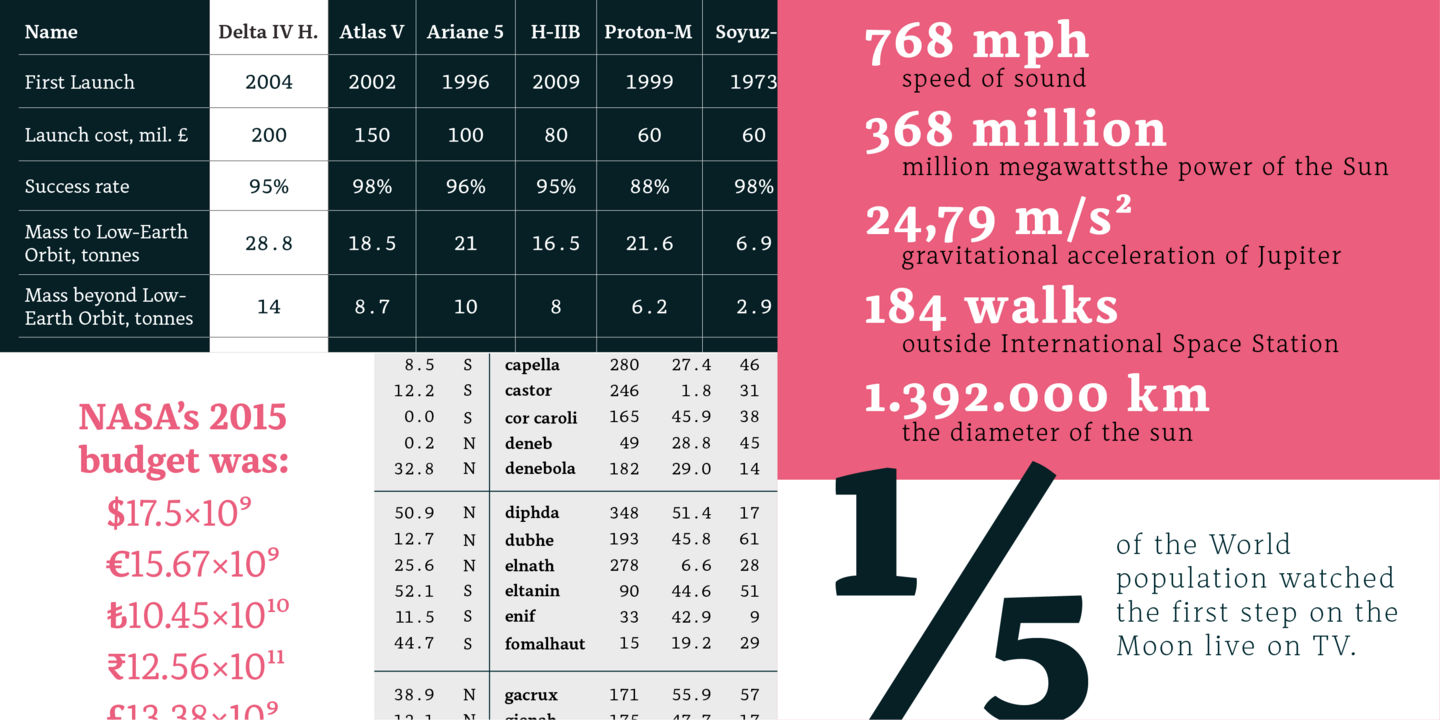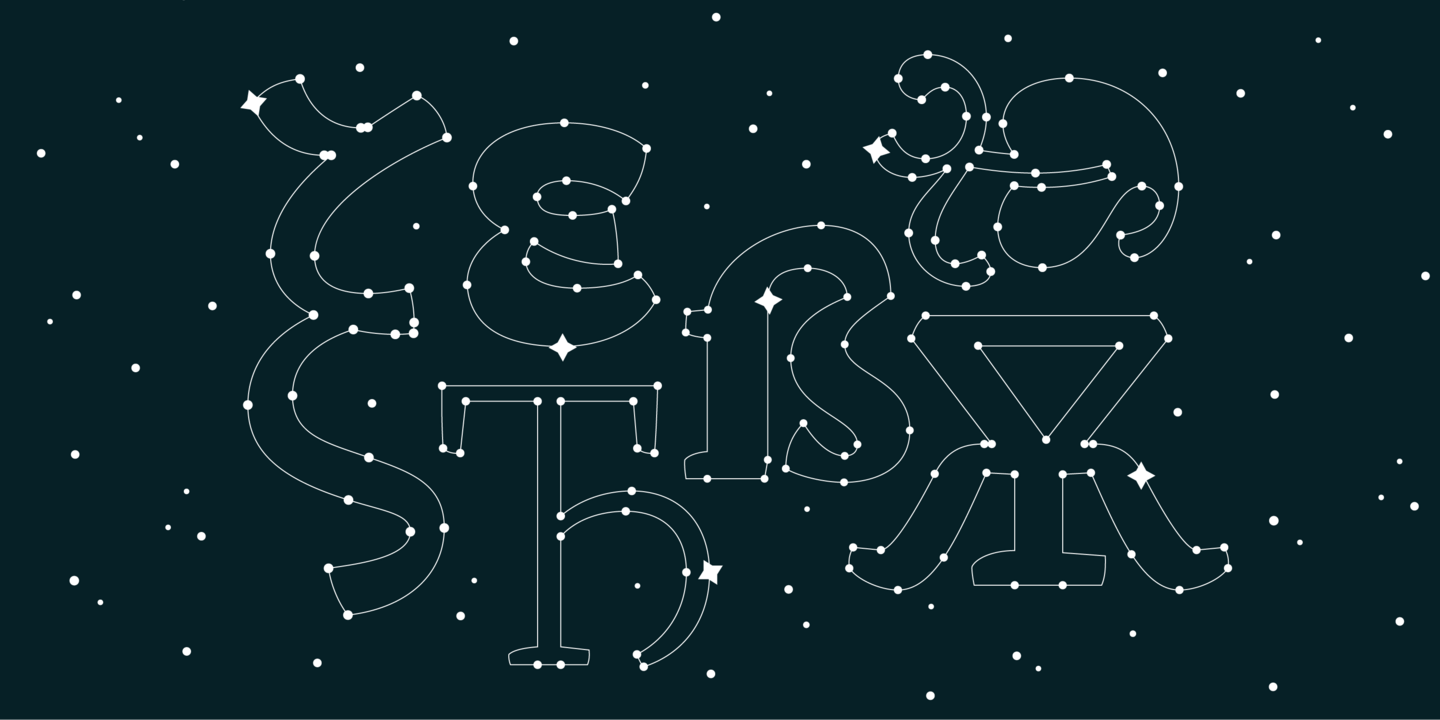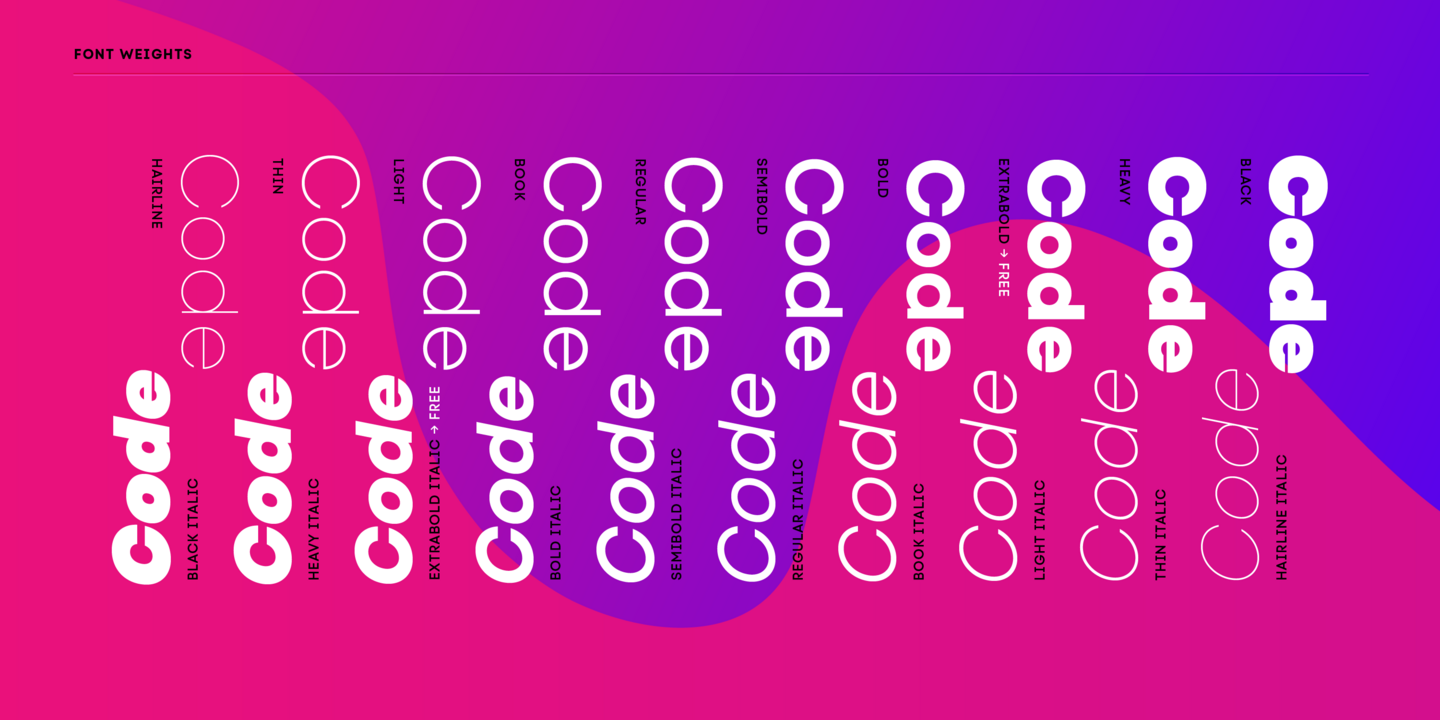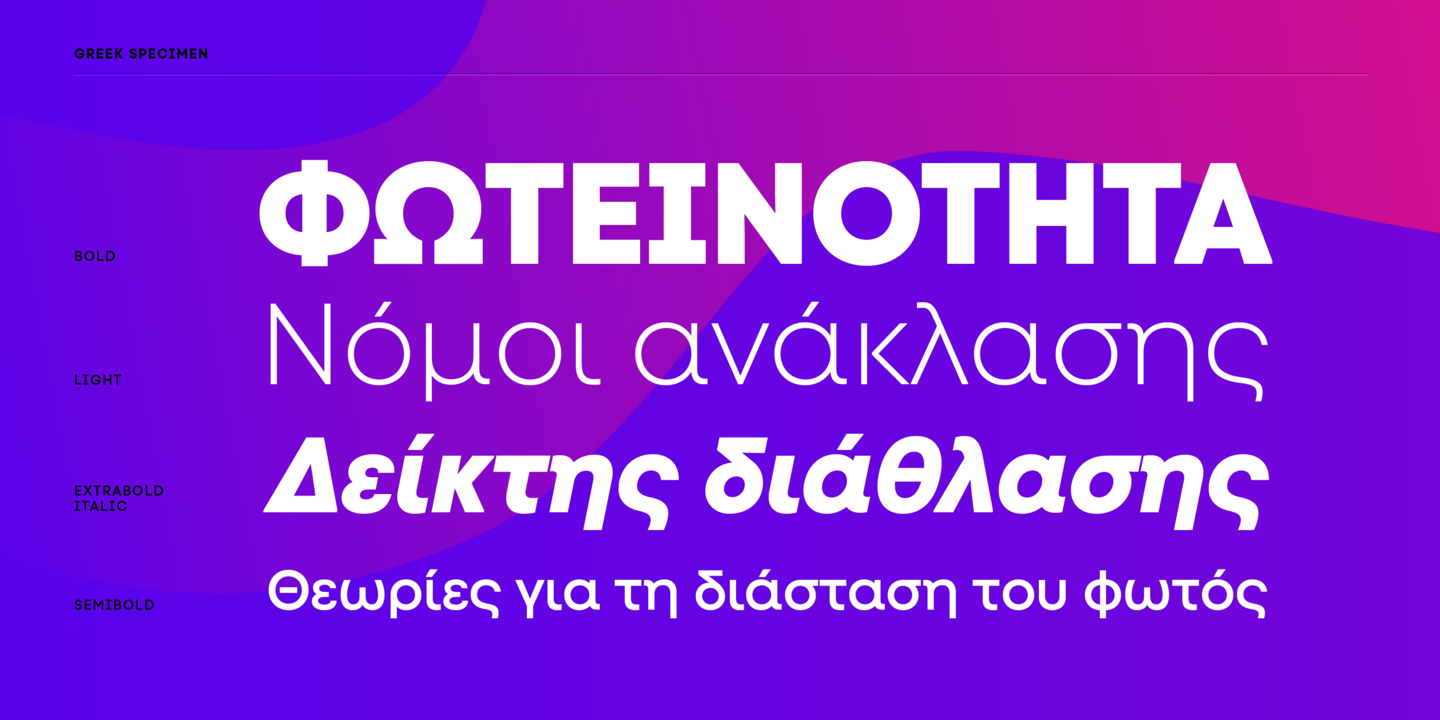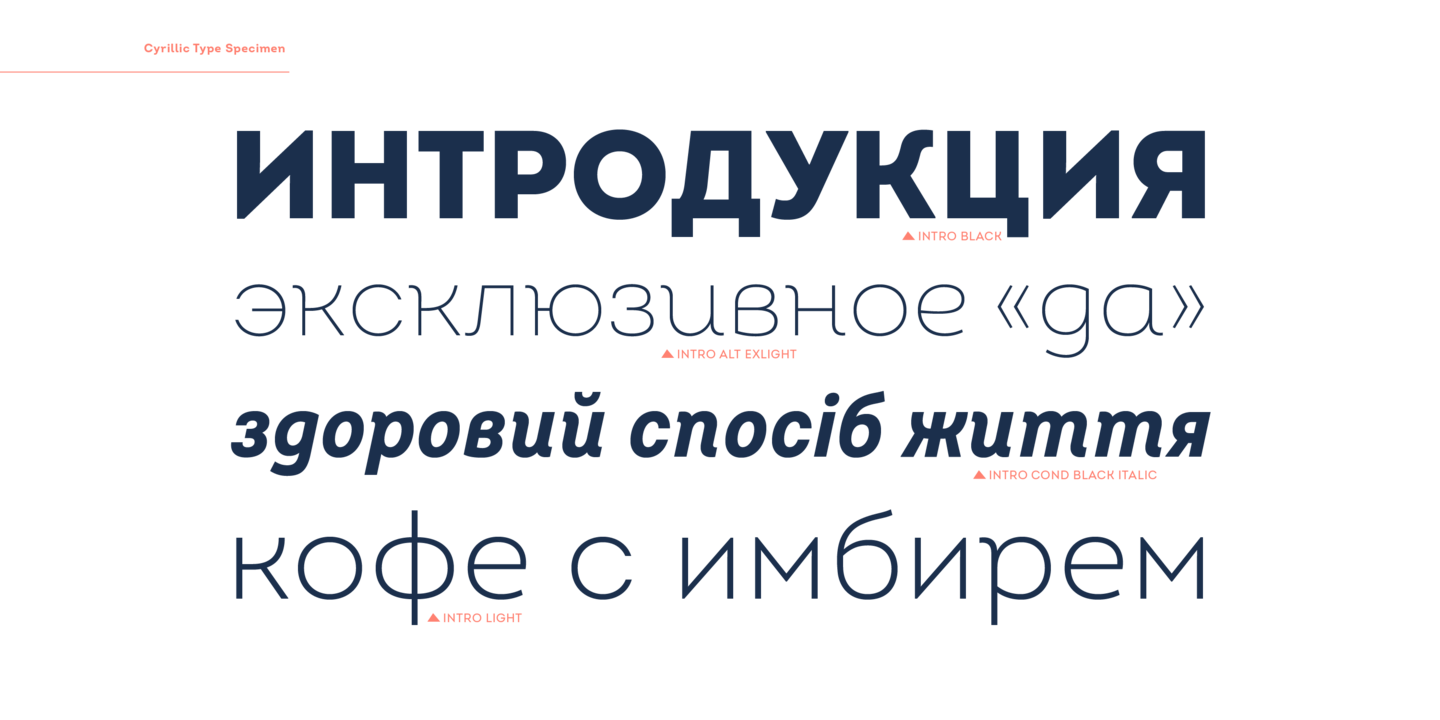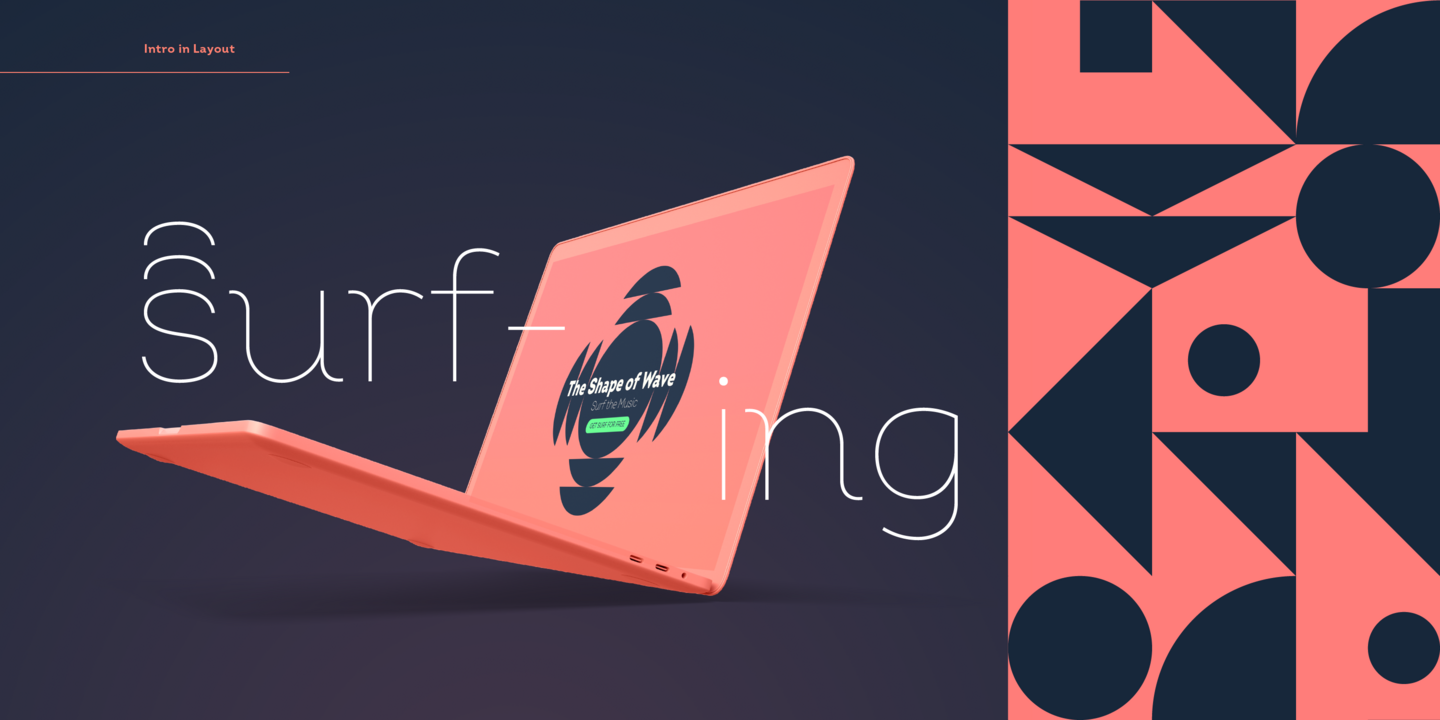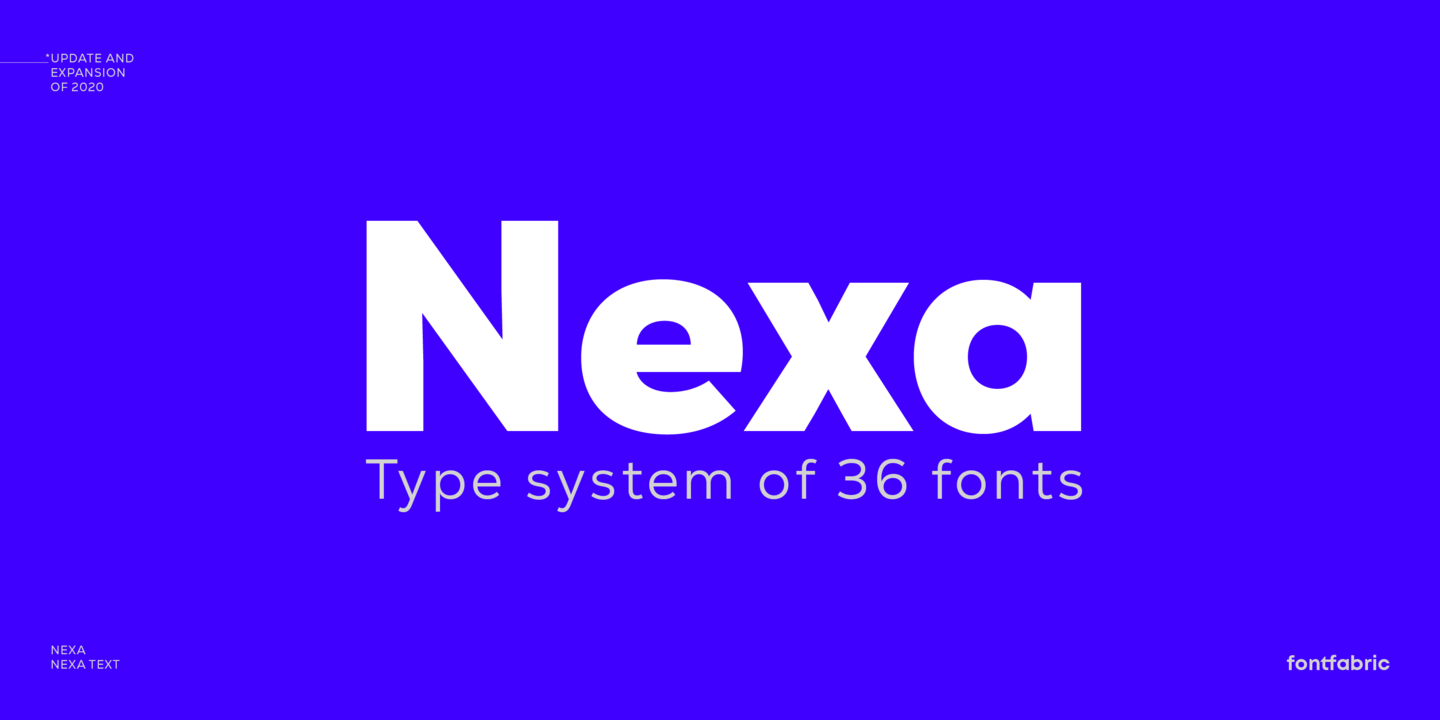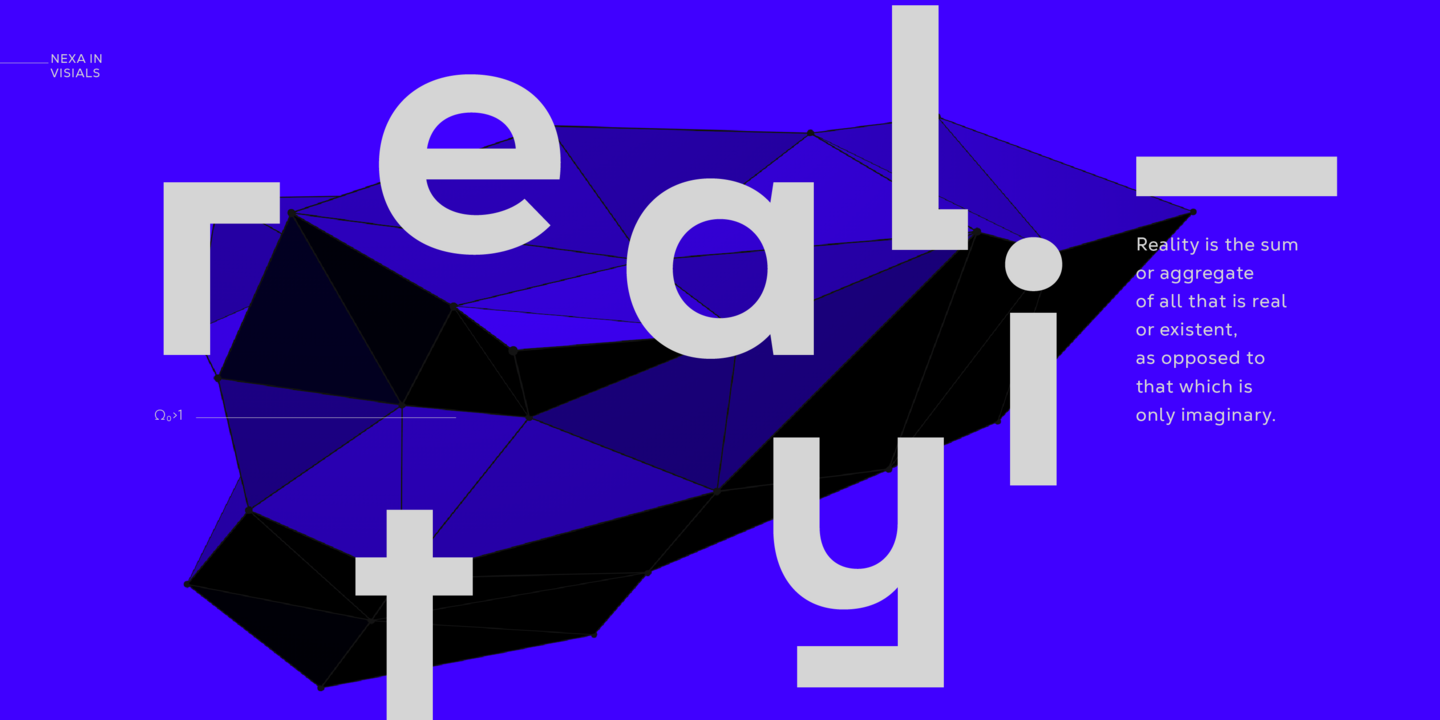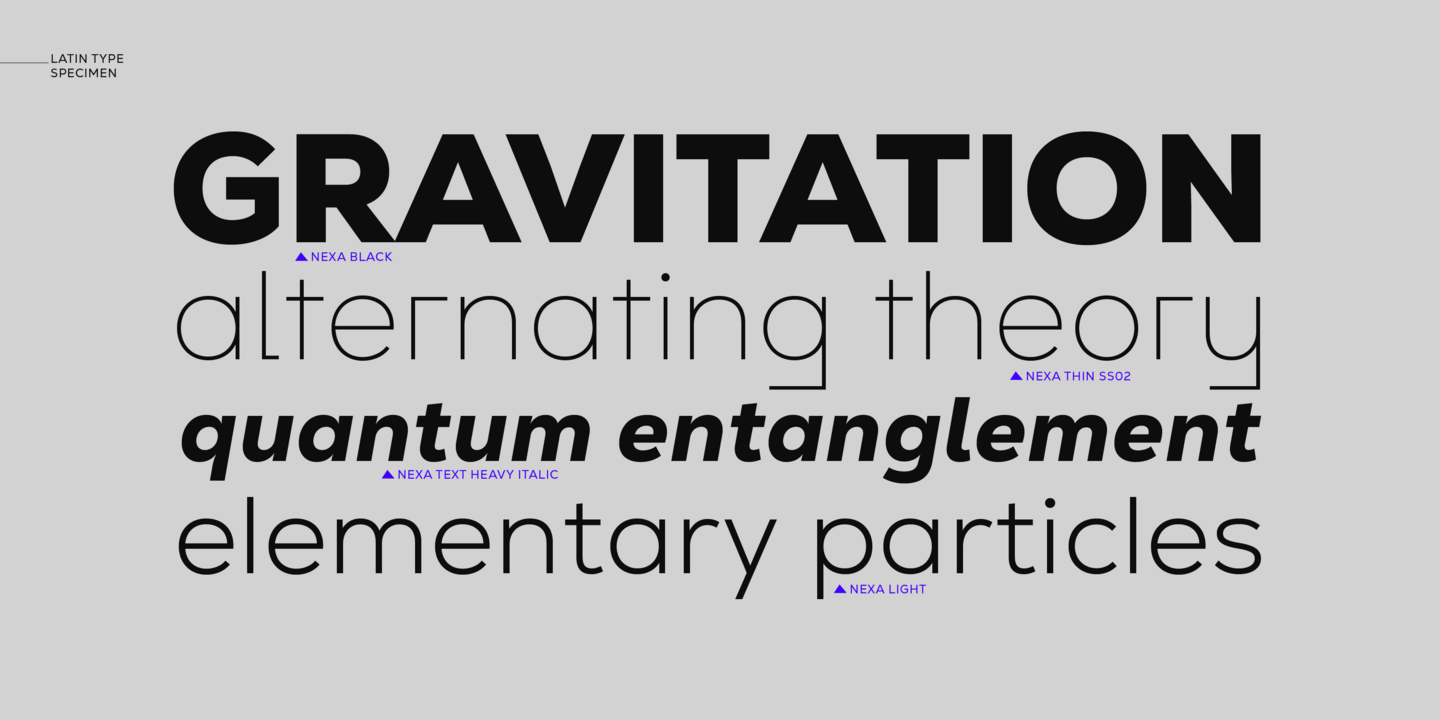
Dernier joyau de notre portefeuille et véritable héritage, le Code Suivante est une évolution stupéfiante du Code Pro en termes de fonctionnalité, de polyvalence et d'application. Ce sans géométrique est conçu pour compléter des pièces de prestige, offrant une large gamme de styles et de graisses, des caractères latins, cyrilliques et grecs étendus, une refonte complète et un raffinement de glyphs , 2 variables polices, pour n'en citer que quelques-uns. Les formes audacieuses et simplifiées du Code Suivantes'adaptent à toutes les conceptions modernes pour l'impression, le web et la visualisation, ce qui en fait l'une des préférées de votre collection police .
Nexa, l'une des polices de caractères géométriques les plus connues de notre époque et récemment complètement raffinée, est proposée avec un total de 36 styles police , une toute nouvelle sous-famille Nexa Text, un ensemble stylistique futuriste à des fins d'affichage et une fonctionnalité inégalée. L'aspect unique de Nexa , combiné à une riche variété, le place au-delà de la portée des caractères géométriques ordinaires pour toutes sortes d'échelles et d'objectifs, et des conceptions qui parlent d'elles-mêmes.
Depuis son succès indéniable dès sa sortie en 2018, Mont's a parcouru un long chemin depuis une simple famille de caractères géométriques et s'est même élevé au rang de marque de fabrique de notre marque police. Mont brille avec un total de 22 styles police , un latin, un cyrillique et un grec étendus, un ensemble de fonctionnalités OpenType avancées et des tas de détails uniques, le "t" proéminent étant l'une de ses qualités les plus populaires. La polyvalence et les qualités de ce caractère lui permettent de relever facilement tous les défis de la conception graphique : visuels d'affichage, logos remarquables, composition complexe, et bien plus encore.
Après une révision substantielle, l'Intro ludique a été un best-seller choisi par des millions de créatifs au cours des 8 dernières années. La famille 72-polices offre des améliorations essentielles : distribution des graisses entièrement révisée, extension de la casse des glyphes, extension du latin et du cyrillique avec localisation adéquate, et réécriture de l'ensemble des fonctionnalités OpenType. L'aspect convivial incomparable d'Introest plus visible dans les conceptions d'affichage où ses détails excentriques peuvent être mis en valeur.
Inspiré par les étoiles, Alkes a parcouru un long chemin depuis un projet de fin d'études jusqu'à une famille de caractères à empattement multi-scripts publiée. Conçue dans le but d'harmoniser les trois écritures - latine, cyrillique et grecque, cette police de caractères humaniste bien définie combine le meilleur des mondes numérique et analogique. Si vous recherchez une structure claire, une hiérarchie et des écritures non latines cohérentes pour l'impression et les environnements à l'écran, Alkes est la voie à suivre.
Avec ses 4 sous-familles impressionnantes, le pack Intro Rust est l'un des plus gros packs du marché, incluant un total de 214 polices. Un magnifique mélange de display, de rust et de script, cette police de caractères vous servira à créer tous types de designs tels que des documents imprimés, des designs web, des marques, et bien plus encore. Laissez libre cours à votre imagination, Intro Rust se chargera du reste.
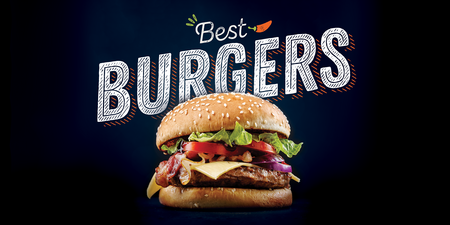
Directeur créatif de type
Plamen Motev
Également connu comme le directeur de la typographie qui vit pour les aspects intellos de la technologie police . Au-delà de son dévouement quotidien à la vente au détail et aux projets personnalisés des clients, Plamen est toujours prêt à relever des défis et voit chacun d'entre eux comme une occasion de s'aventurer en territoire étranger et d'apprendre quelque chose de nouveau. Une de ses missions personnelles est de guider ses collègues typographes, étudiants et stagiaires tout au long de leur parcours dans le monde de polices.
Concepteur de type
Nikolay Petroussenko
Niki enseigne à l'Académie nationale des arts de Bulgarie et est officiellement déclaré comme le dessinateur de caractères qui parle le plus de langues au monde. Ce deuxième titre lui est gracieusement accordé par ses collègues. Le plus souvent, vous trouverez Niki en train d'étudier et de travailler sur les cultures étrangères et leur patrimoine écrit. Grâce à son approche passionnée des écritures exotiques, Fontfabric parle la langue de n'importe quel client.
Concepteur de type
Ventsislav Dzhokov
Passionné de calligraphie et de lettrage, Ventsi se consacre à l'amélioration de la qualité de chaque script police. Doté d'un grand sens de la typographie et de la persévérance d'un millier d'hommes, il transforme une simple page police en un projet fonctionnel grâce à la magie d'OpenType. Il est de notoriété publique que la nature productive de Ventsi nous aidera un jour à découvrir un moyen d'allonger la journée.
Super-femme à l'humour piquant, Iva vient de la publicité, où elle a mélangé ses formations en graphisme et en gestion de marque. Depuis ses années d'université, elle nourrit un lien particulier avec le métier de typographe et, dans un moment d'introspection, elle a décidé de se consacrer à sa véritable passion. Quatre années de nombreux ateliers plus tard, Iva a atteint un point d'autosatisfaction avec ses nouvelles compétences et a trouvé sa place en tant que dessinatrice de caractères officielle chez Fontfabric.